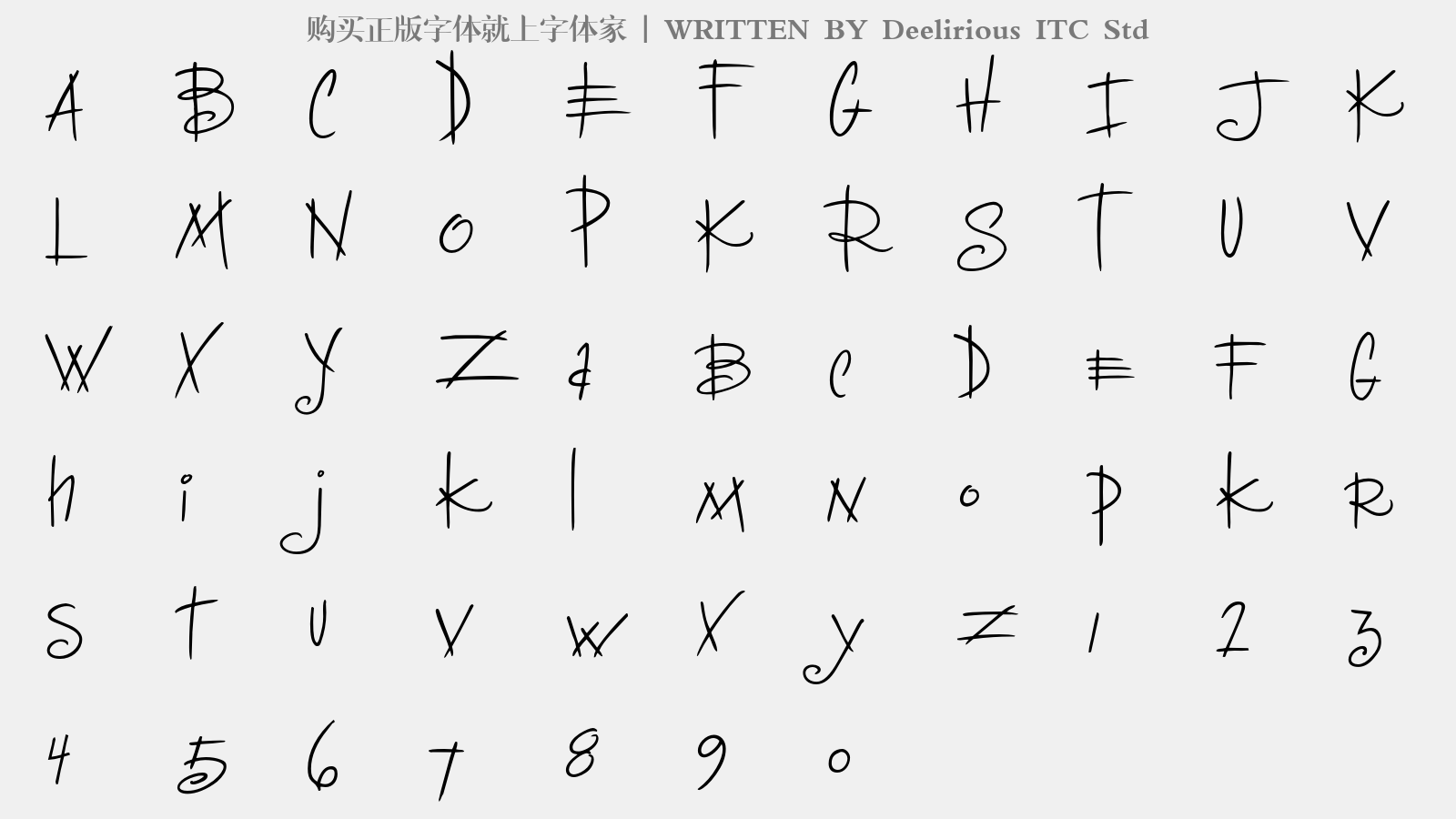
Deelirious ITC Std
字体作者:现代字体
字体名称:Deelirious ITC Std
字体字数:26个英文大小写字母及和阿拉伯数字
书体类型:英文类
Deelirious ITC Std
该字体是一款个性独特的英文字体,非常适合创意类的PS字体,英文广告设计载体上使用,在设计中选择这款字体应用的话,会起到非常理想的效果。